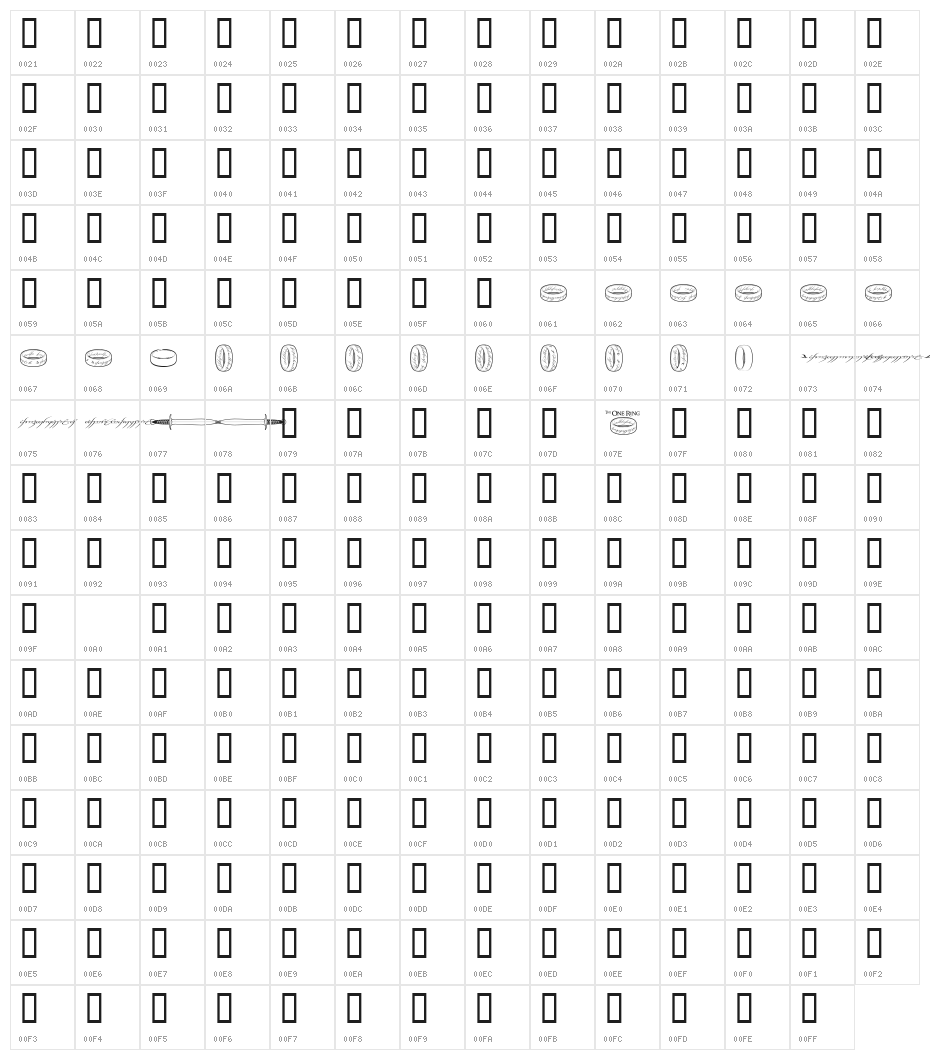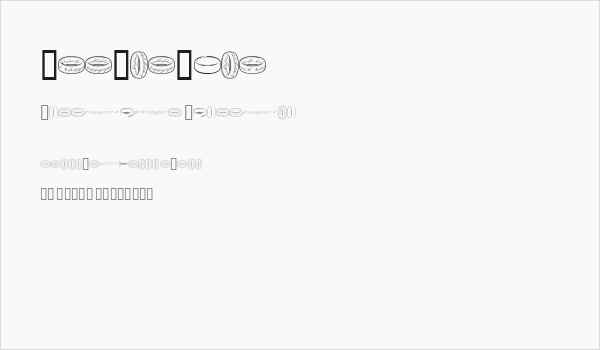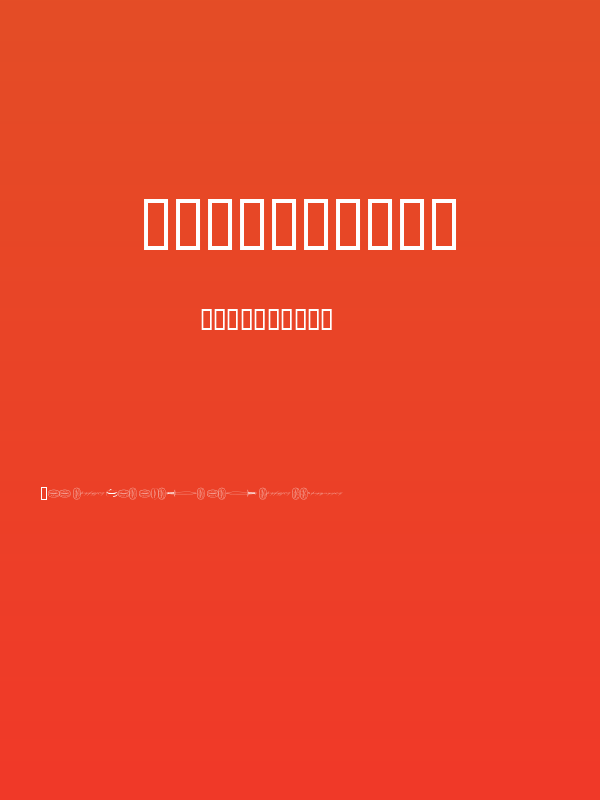
TheOneRing Font
| Caso d'uso | Decorative artwork, Themed graphics |
| Progetti proposti | This design could be used for decorative purposes, such as themed artwork or fantasy-inspired graphics. |